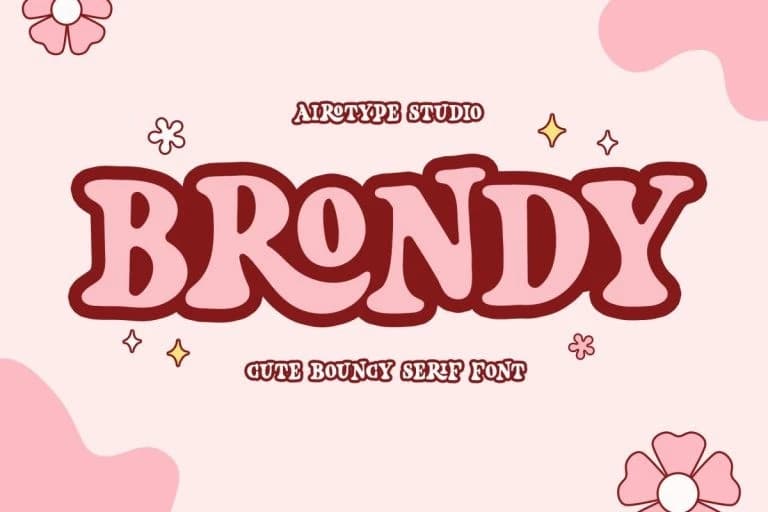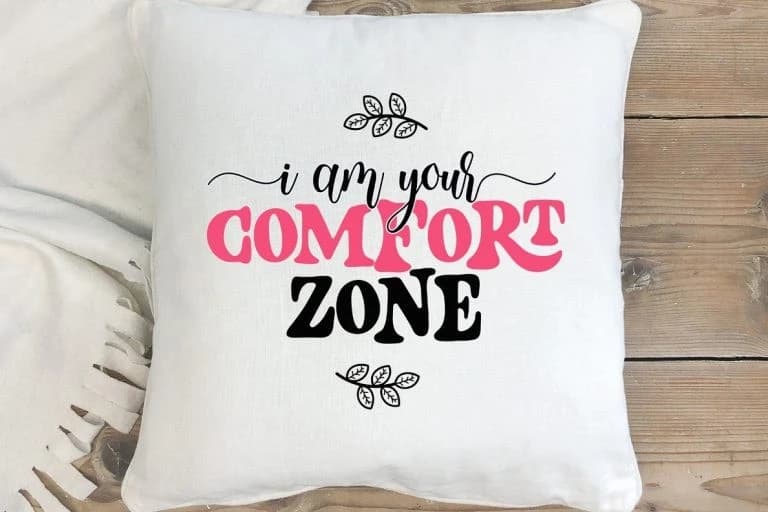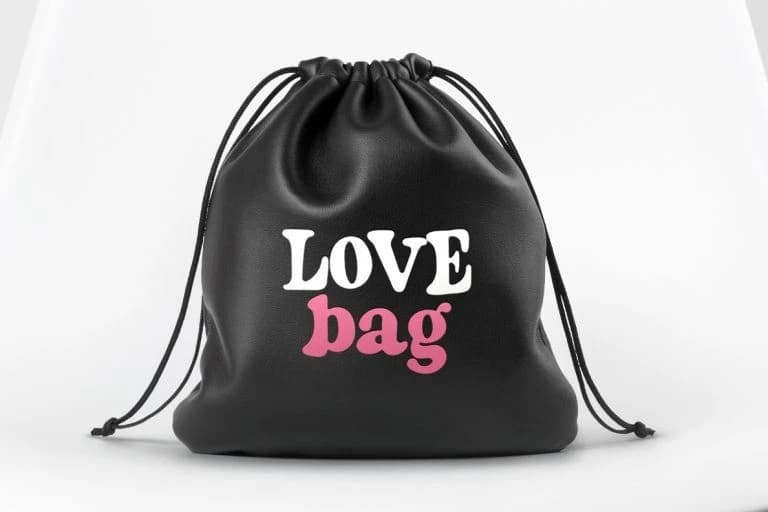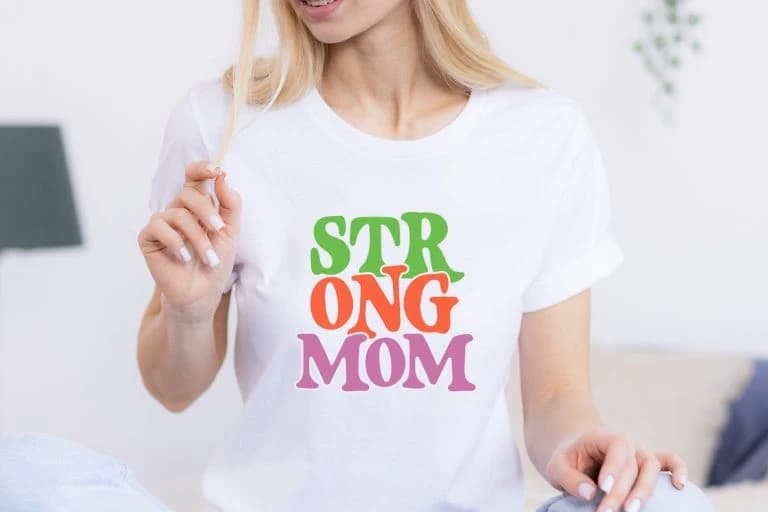
Brondy Display Font
Brondy Display Font, sevimli bir retro serif fontudur. Vintage, groovy ve eğlenceli bir stile sahiptir. Tasarımda daha fazla seçenek sunmak için bazı büyük harf ligatürleri içerir. Bu font, sevimli ve retro stile ihtiyaç duyan tasarımlar için tatlı bir fonttur; örneğin okula dönüş tasarımları için.
Brondy Display Font, sevimli retro bir serif yazı tipidir. Nostaljik, groovy ve eğlenceli bir tarza sahiptir. Büyük harfler için bazı ligatürler vardır; tasarım yaparken daha fazla seçenek sunar. Bu font, sevimli ve retro stile ihtiyaç duyan tasarımlar için tatlı bir fonttur; örneğin okula dönüş tasarımları için.